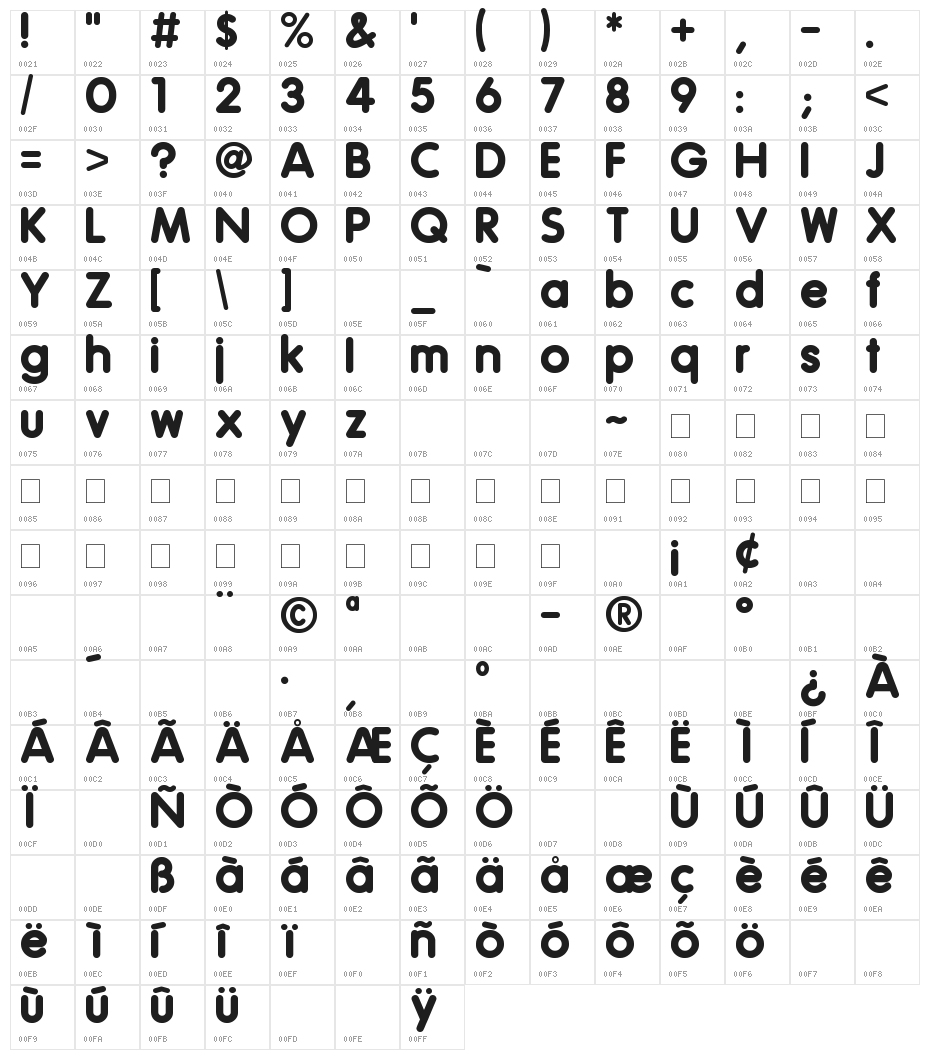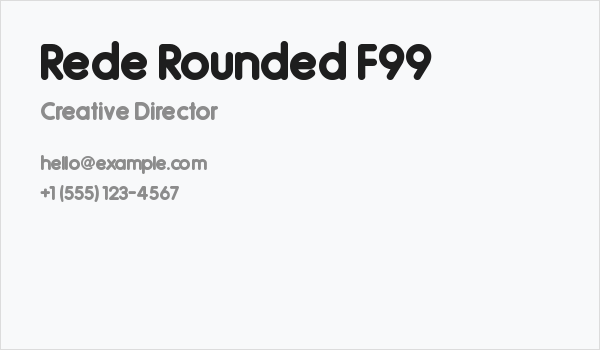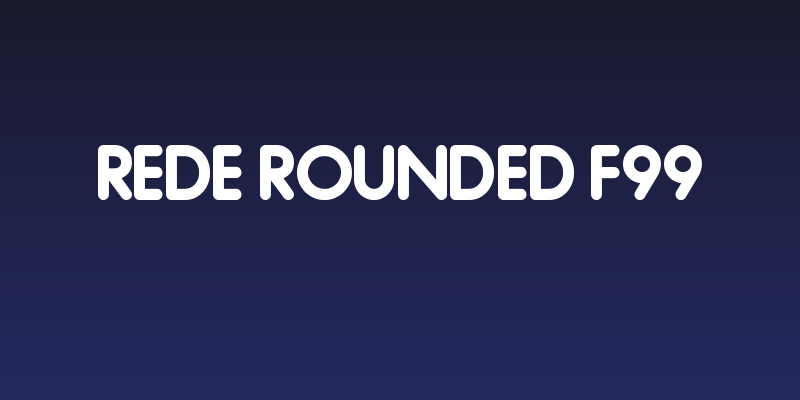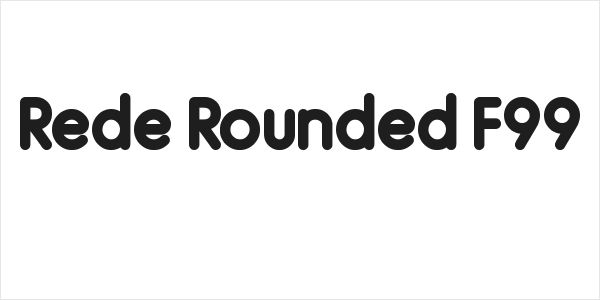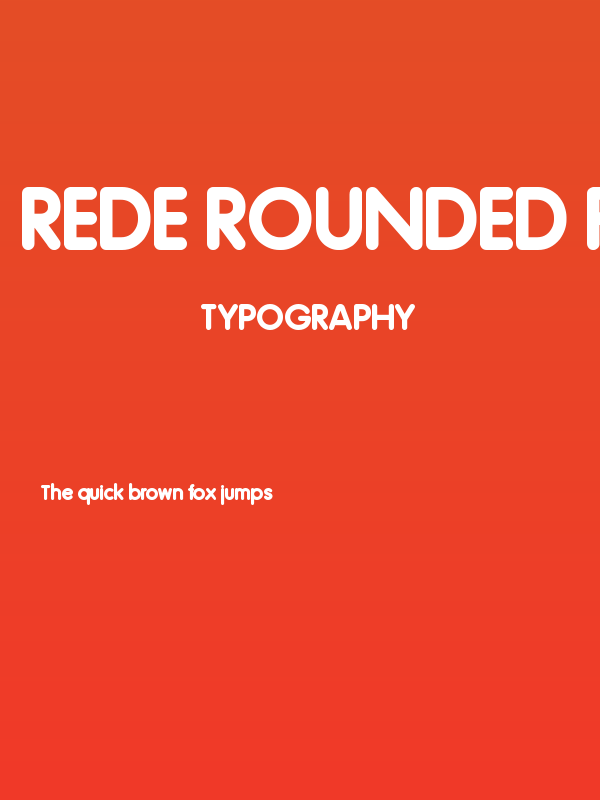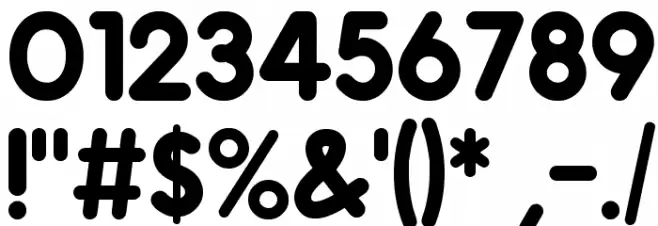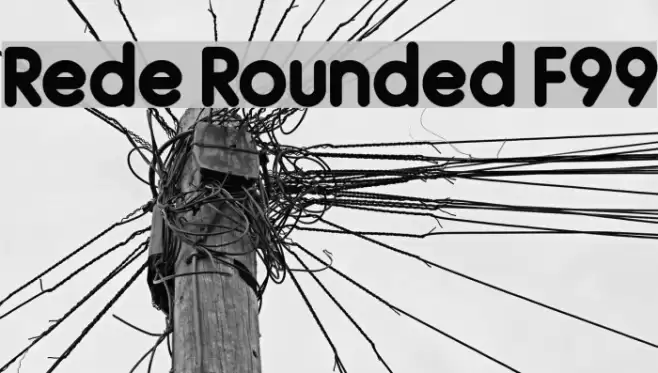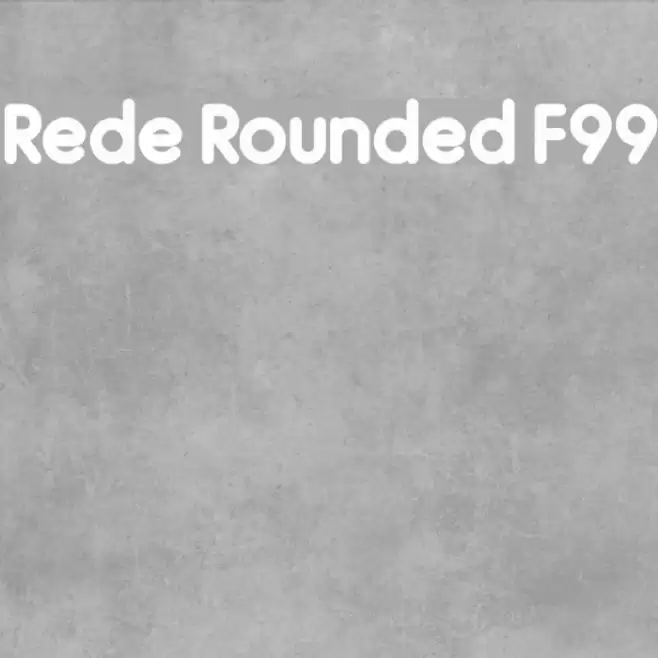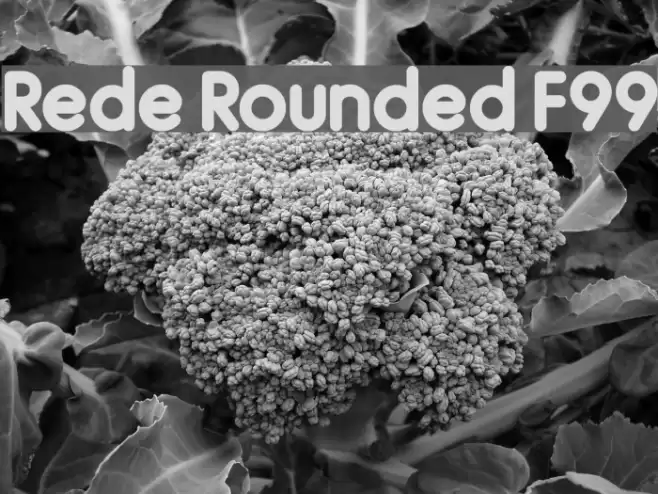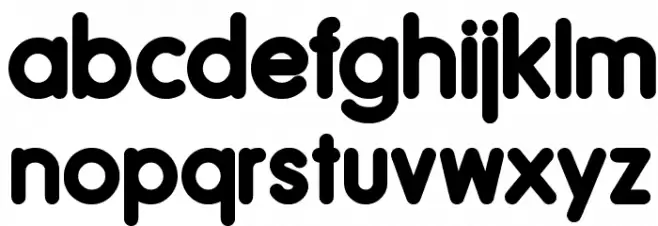
Rede Rounded F99 Font
| उपयोग का मामला | Headlines, Logos, Branding |
| सुझाए गए प्रोजेक्ट | Ideal for branding, advertising, children's books, and digital interfaces where a friendly and modern look is desired. |